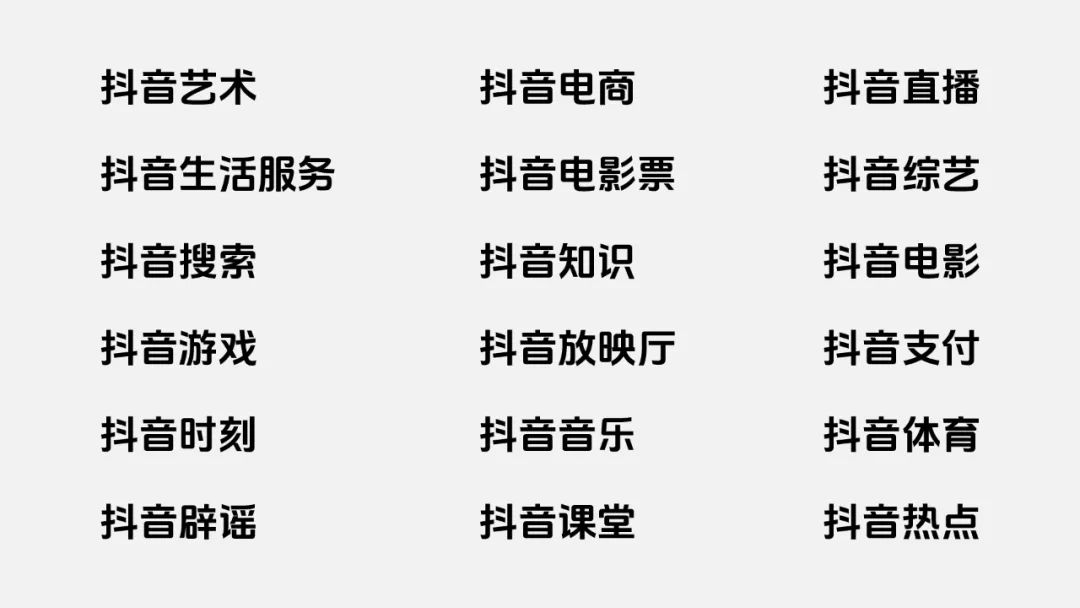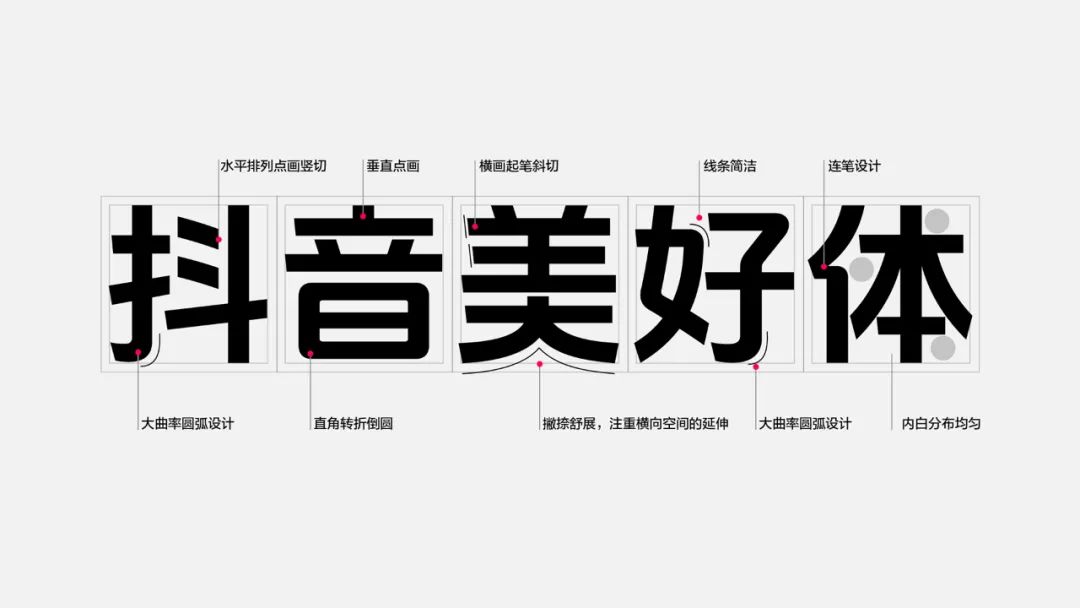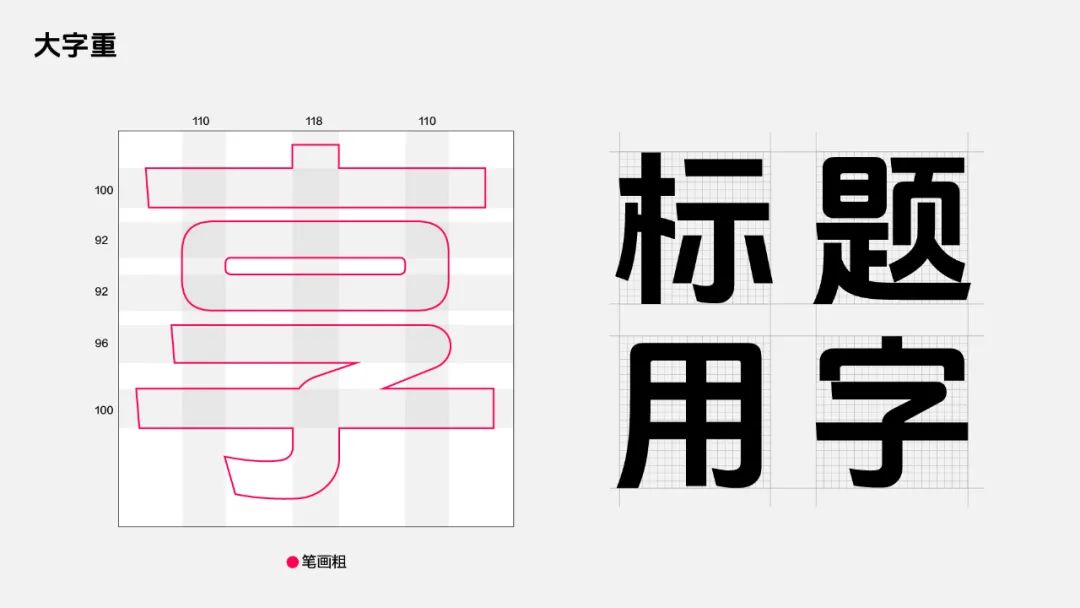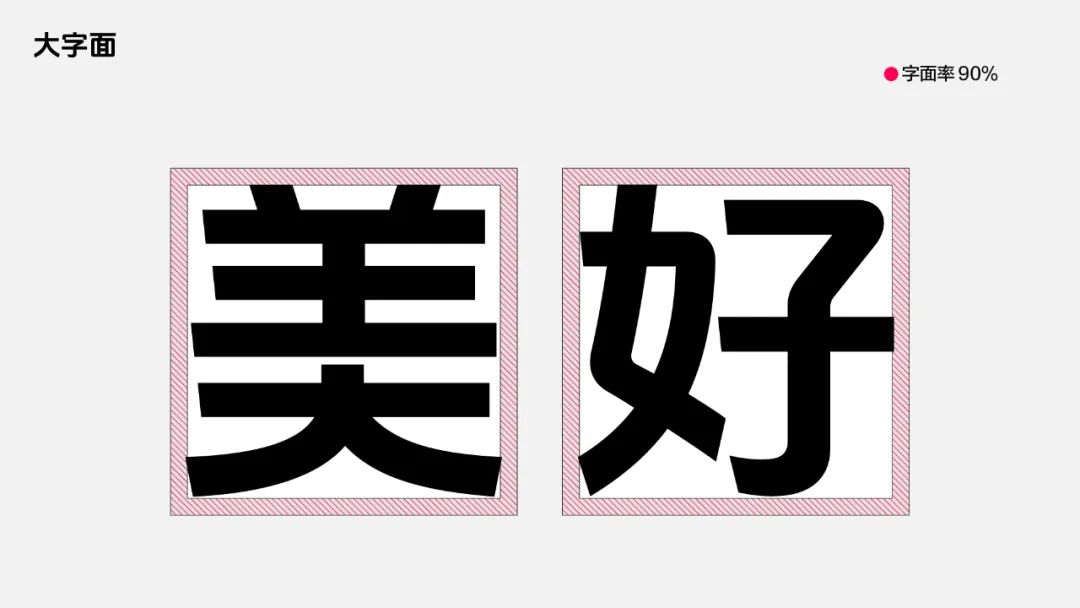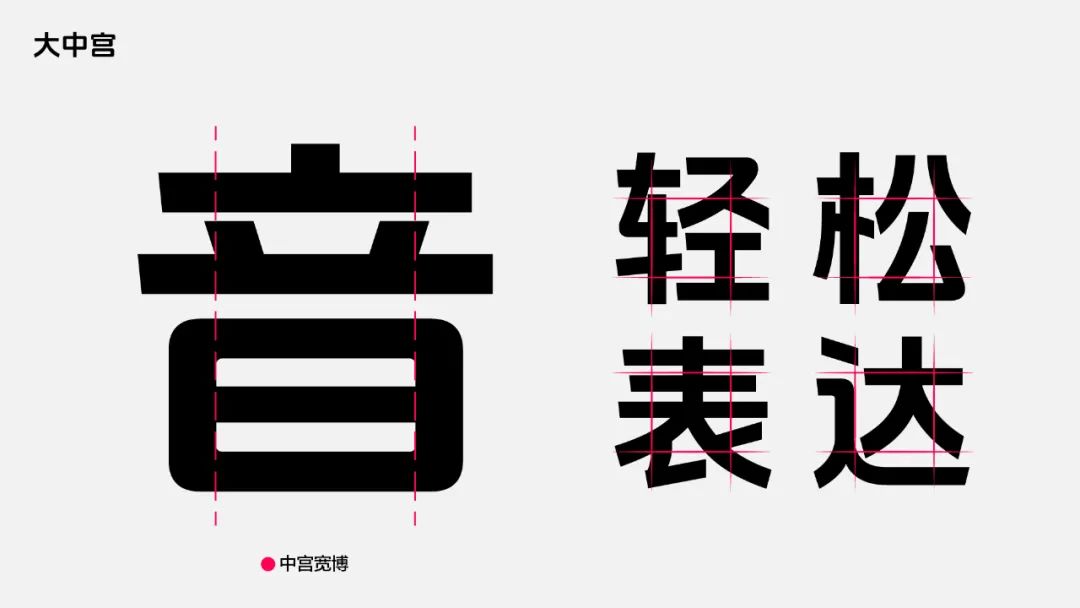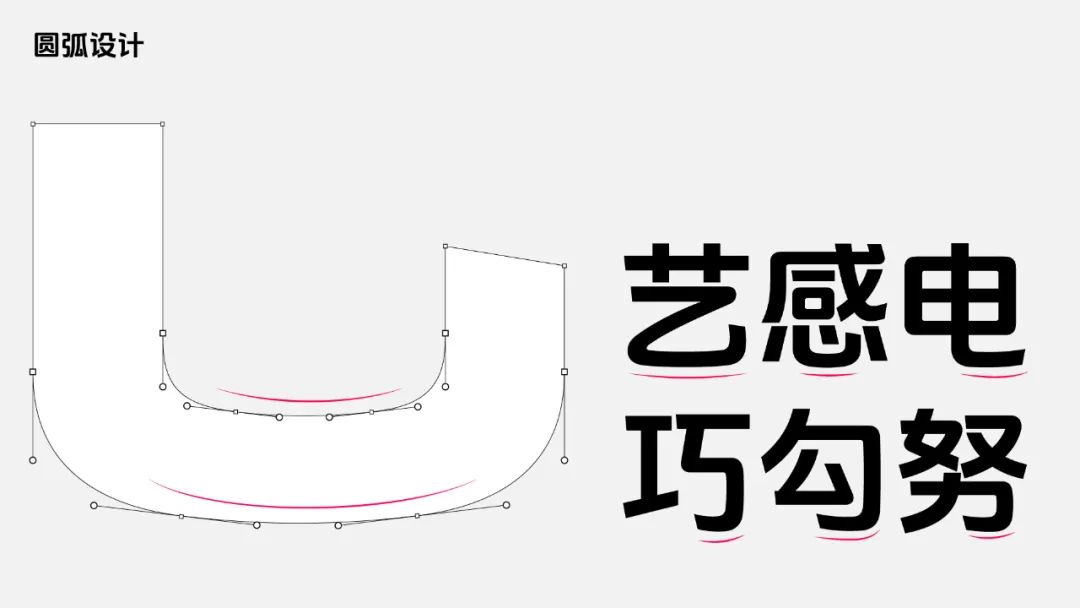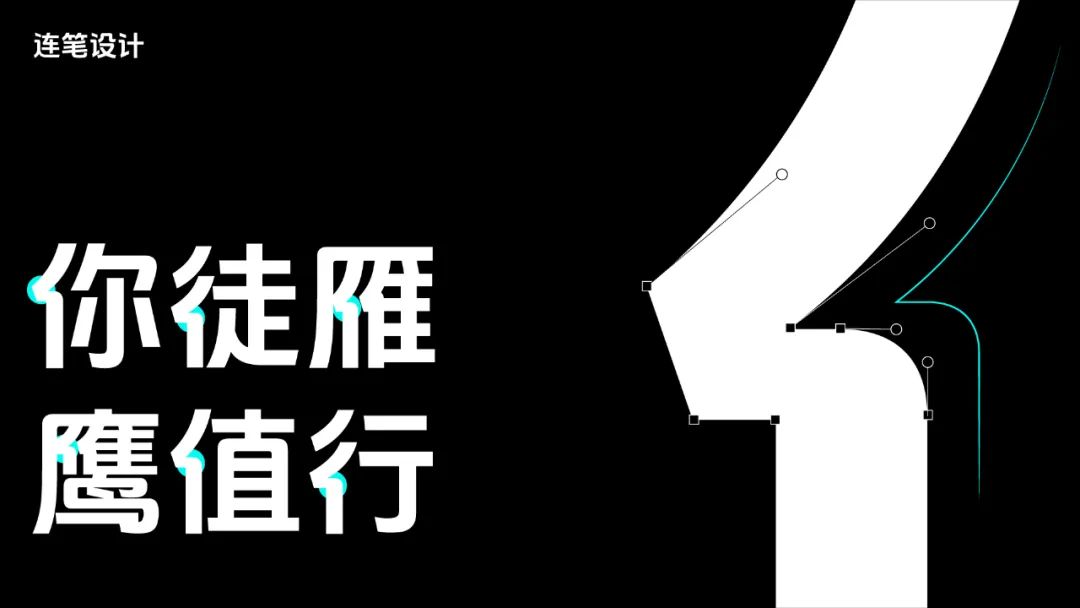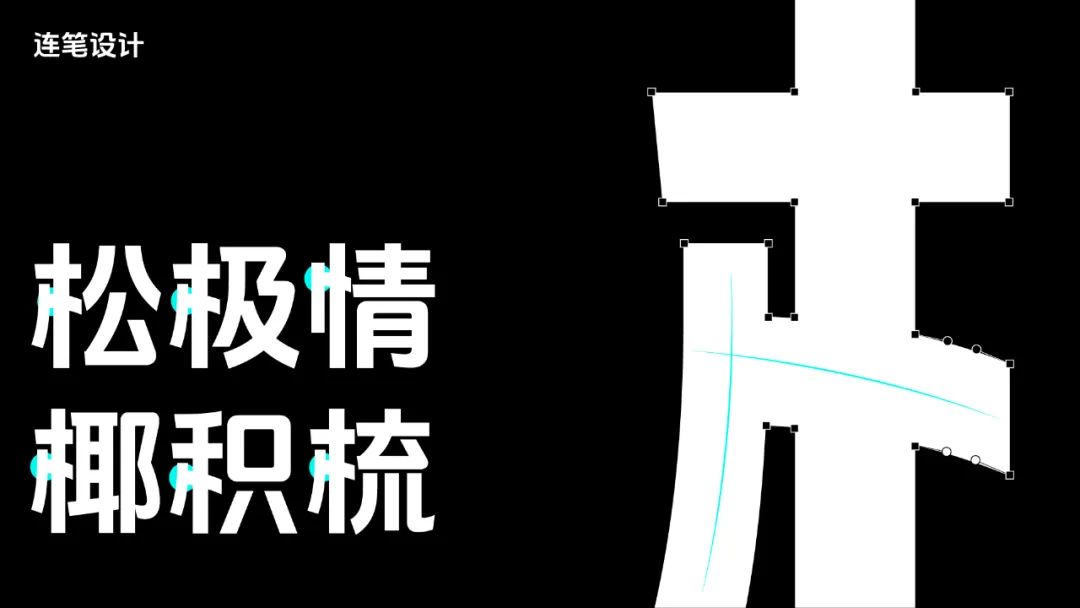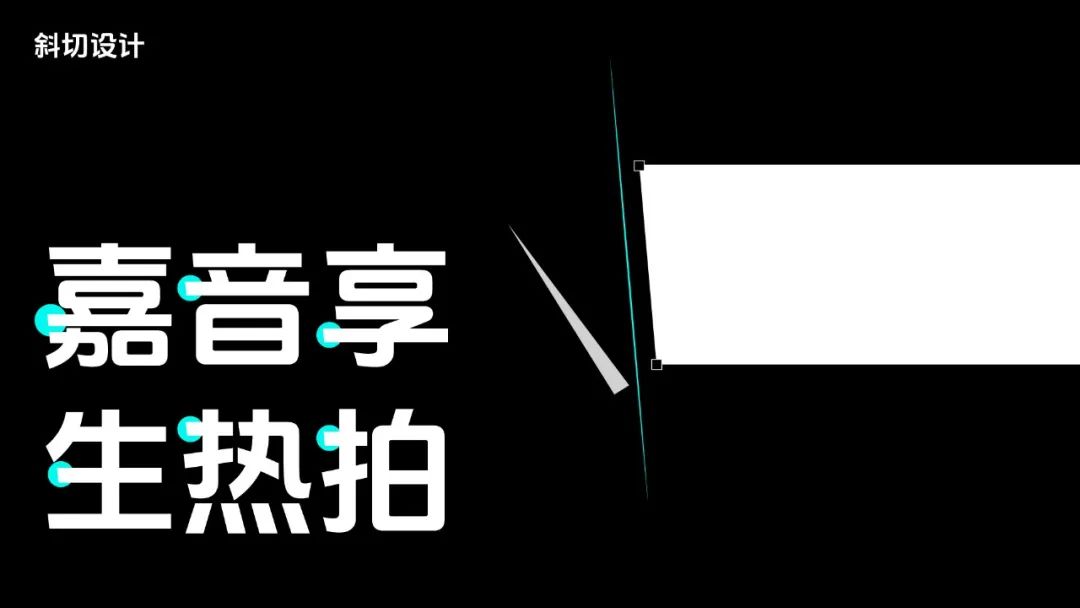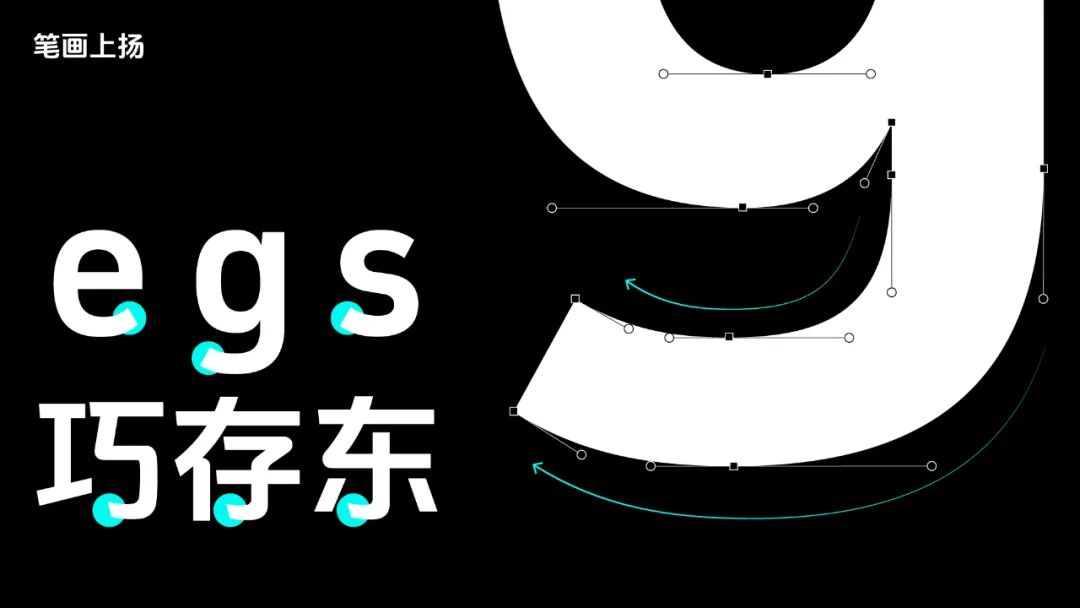
抖音美好体
2023年,抖音从短视频平台发展成为一个多体裁的内容创作和共享平台,为用户带来高质量的内容,鼓励大家轻松创作和分享,发现和传达美。为了更好地传播“记录更好的生活”的品牌理念,更好地满足品牌的长期发展,创造高质量的内容创作和产品体验,抖音体验设计中心和方形图书馆联合设计开发了一个简单大方、清晰易读的品牌定制字体,具有现代气质和文化属性。
tiktok包含6763个中文字符,682个西文和数字符号,执行国家GB2312-80简体中文编码字符标准。抖音作为品牌标准字体,将率先用于抖音及其子品牌,帮助品牌视觉形象的统一,增强品牌的官方性和权威性。抖音美好体抖音美好体抖音美好体
差异化的品牌视觉形象有助于塑造差异化的品牌基调。通过字体骨架建设、笔画细节设计等细节,抖音美丽的身体塑造了“平静、内向、自然、舒适”的字体个性,呼应了抖音带来的“轻松、自然、舒适”的产品体验,传达了抖音独特的品牌基调和感觉。抖音美好体
tiktok提取了“tiktok”logo字体简洁清新的风格特征。为了适应标题场景的使用,它被打造成笔画较厚的大字重字体;90%的大字面率呈现出美观、大方、清晰、易读的视觉风格;大中宫的设计使字体更加舒展饱满,字体具有很强的识别特性。抖音美好体抖音美好体抖音美好体
为了构建品牌字体的独特性,tiktok的笔画细节采用了非常规的弧形设计和倒角设计。弯曲笔画采用大曲率弧形曲线。均匀光滑的线条设计使字体更加流畅、美观、视觉韧性。在平衡字体易读性和识别性的基础上,折叠笔画采用内直外弧的倒角方式,传达“刚柔并济”的人文氛围。
书法是中国传统文化的重要组成部分,笔画、结构、布局等元素都蕴含着丰富的文化内涵和审美价值。tiktok将传统书法文化中的写作感、流畅感与现代字体设计相结合,借鉴行书中连笔写作的精髓,形成独特的连笔设计,将“灵活流畅、自由收放”的视觉体验与tiktok“轻松、自然、舒适”的产品体验相结合。
抖音美体也借鉴了书法中笔锋的概念,将“露锋”笔法转化为水平笔斜切的设计技术,同时保留了写作感,增加了字体的视觉变化节奏。
为了满足抖音整个生态场景的标题使用需求,抖音美丽的身体搭配了几何风格的西方字符,简洁、现代、时尚,同时延续了中国弧和水平笔画斜切割的特点,中西文匹配呈现出一致的视觉气质。抖音美好体抖音美好体
抖音体验设计中心团队将西文和数字字符扩展到五种不同的厚度和宽度,以更好地以品牌赋能产品和业务,满足抖音端不同场景的字体应用需求,提高字体和产品场景的适应性。除了全面推出抖音端的核心场景外,抖音美体还广泛应用于抖音市场传播场景,并嵌入了剪辑、醒图等产品,抖音美体将继续帮助业务发展。